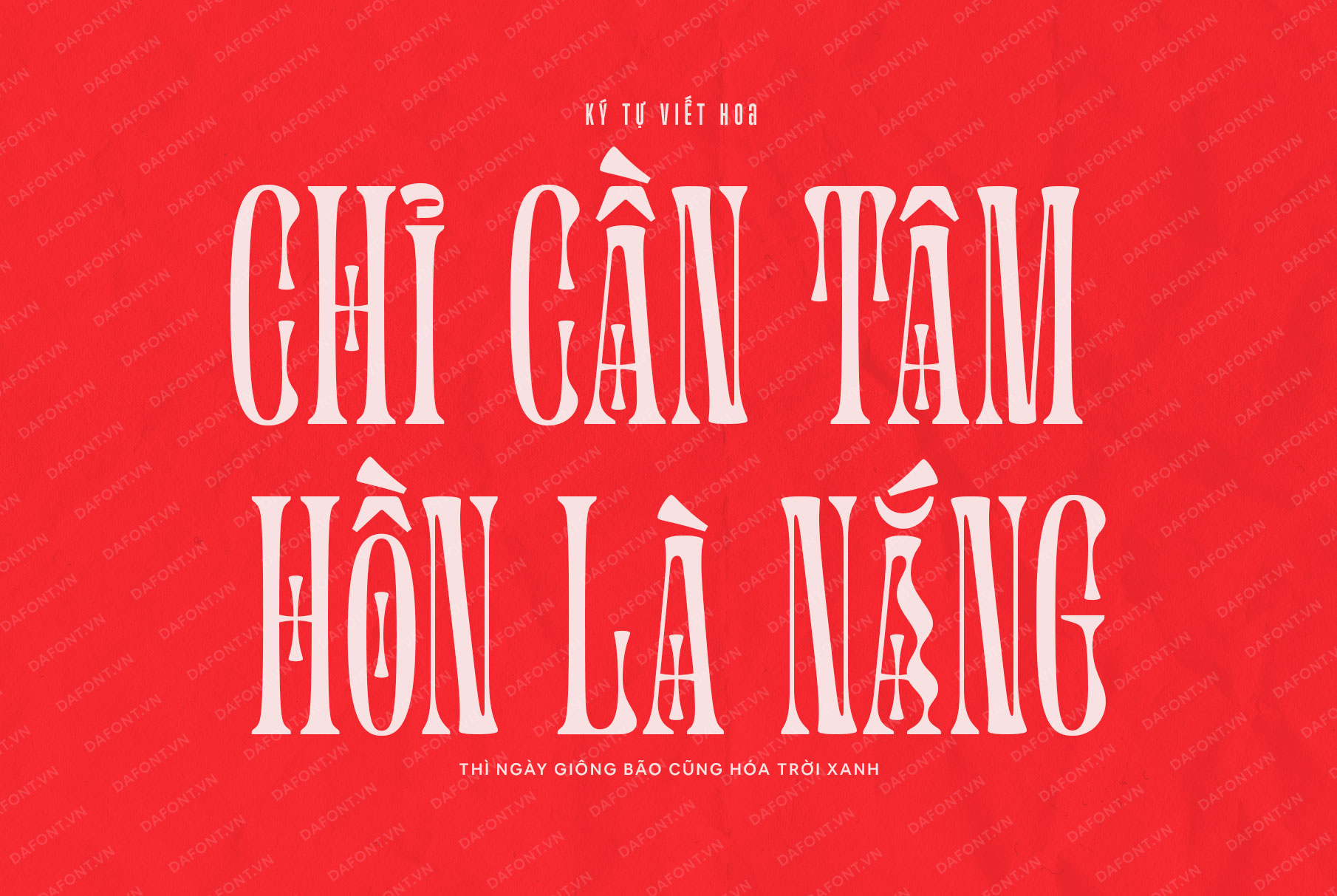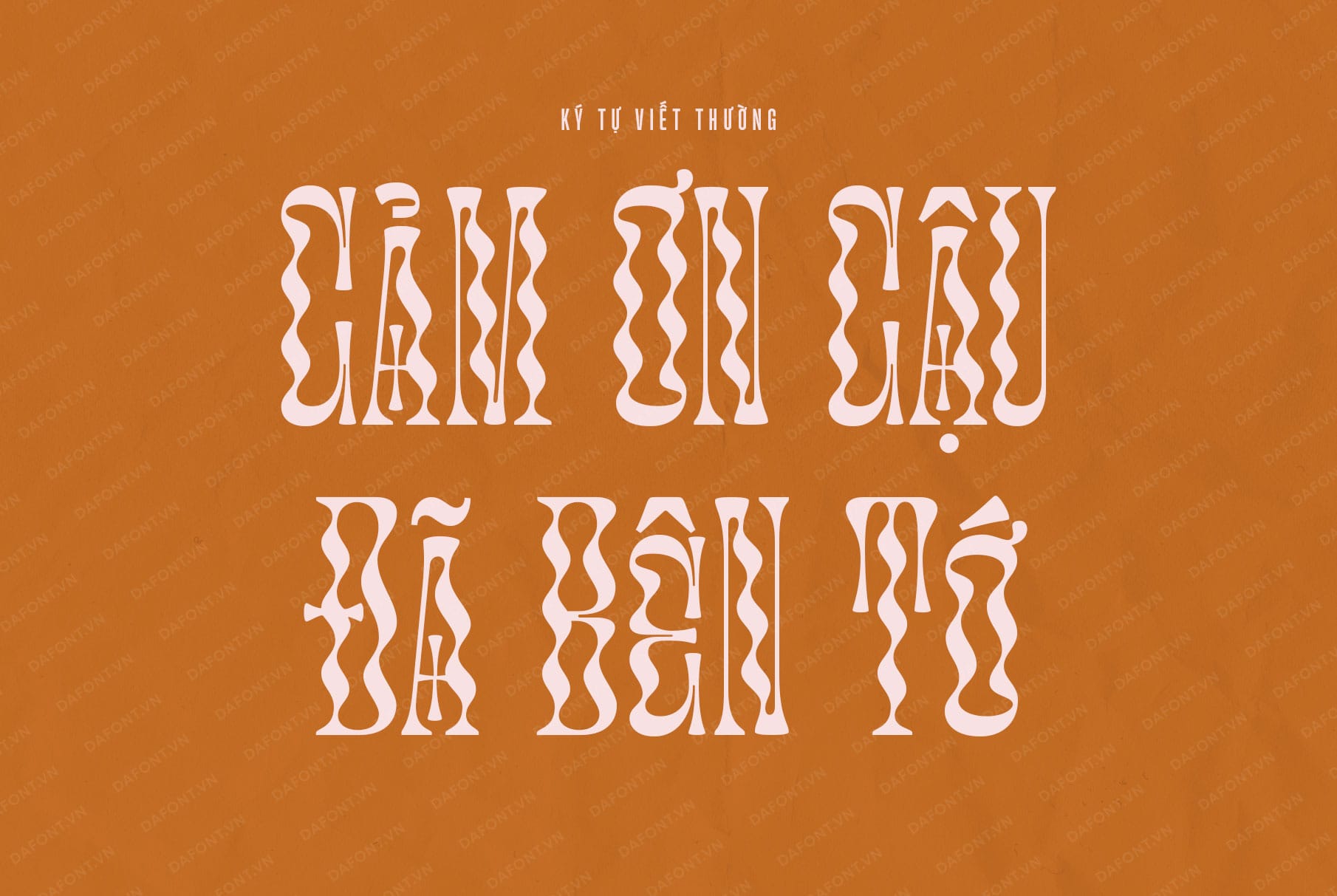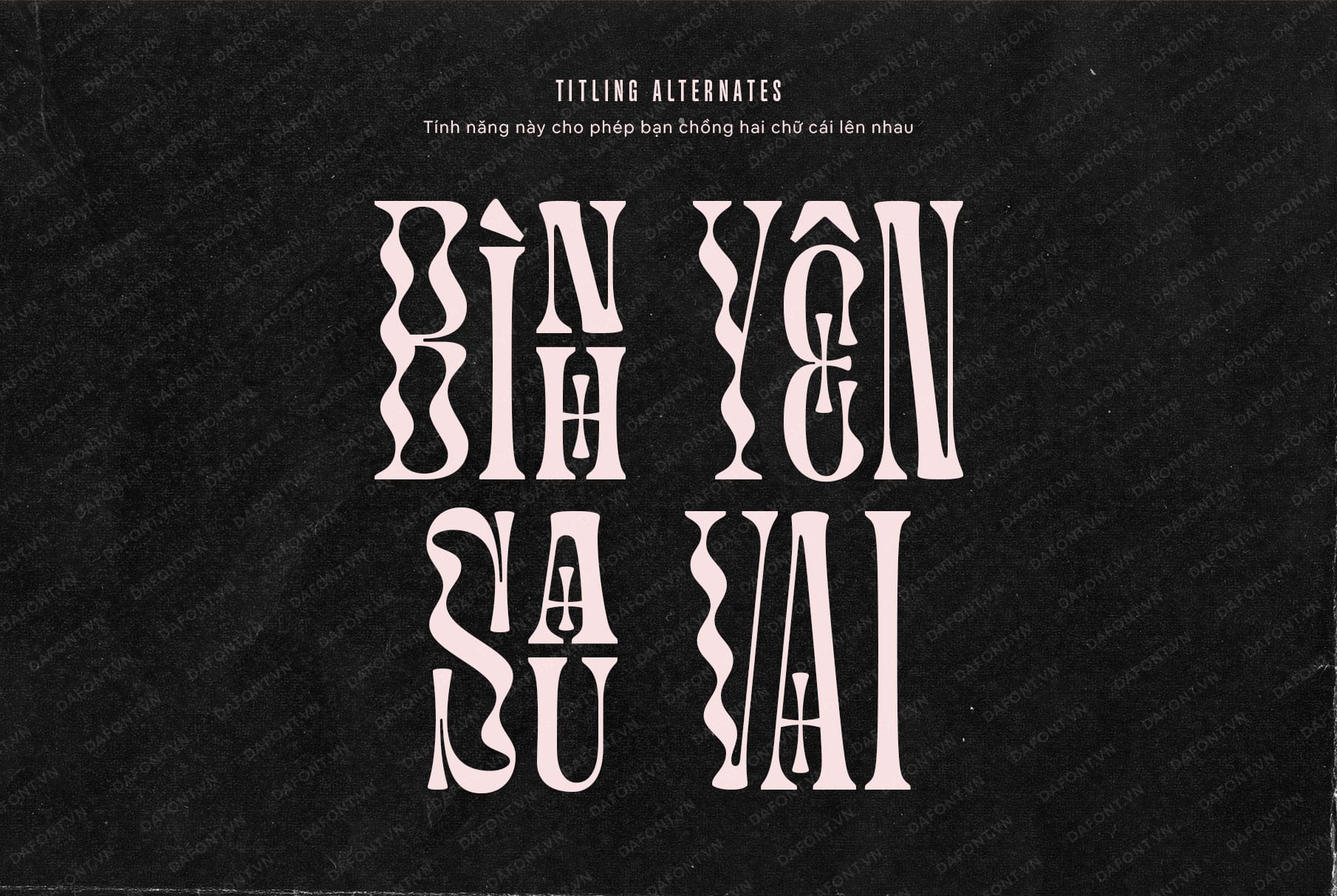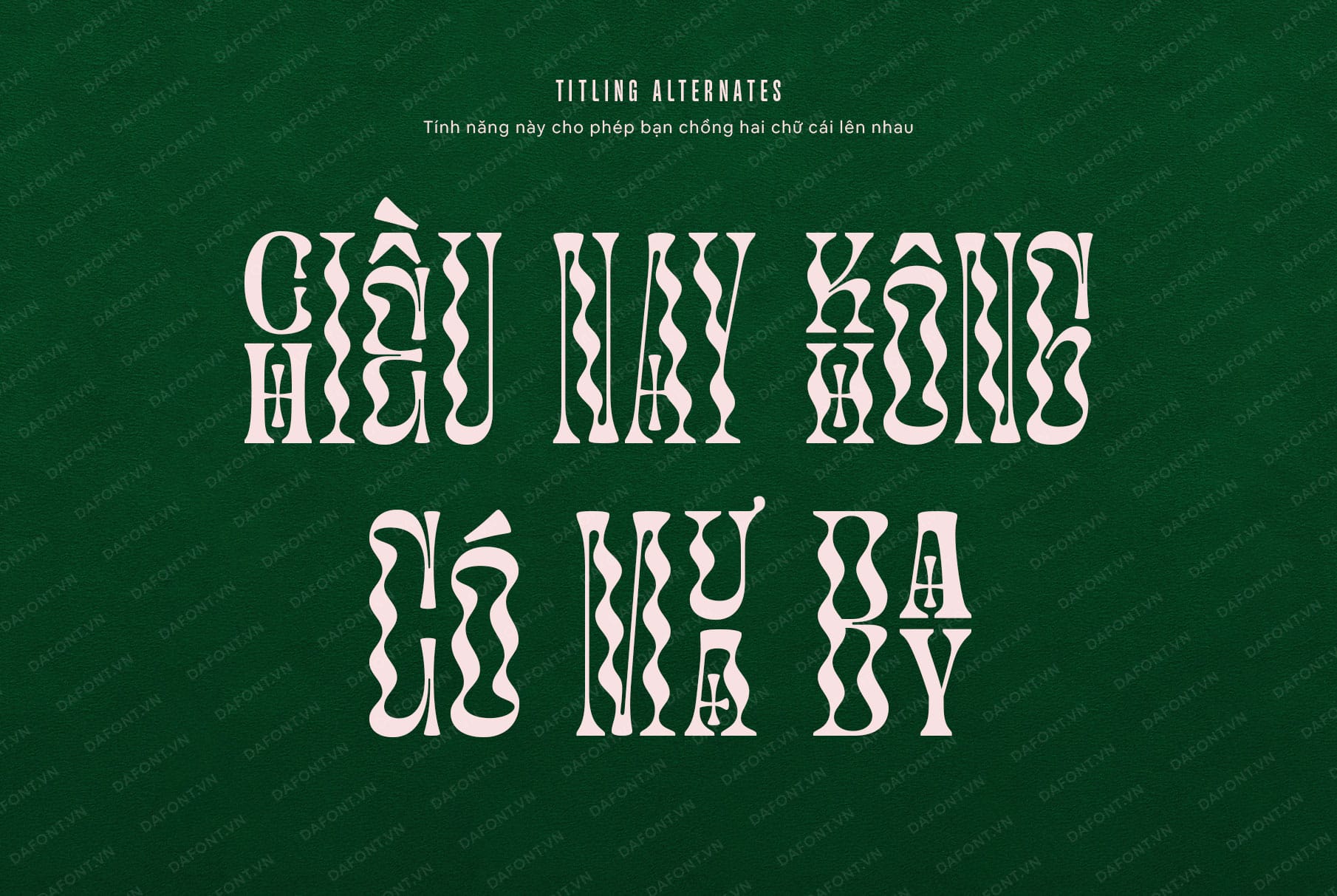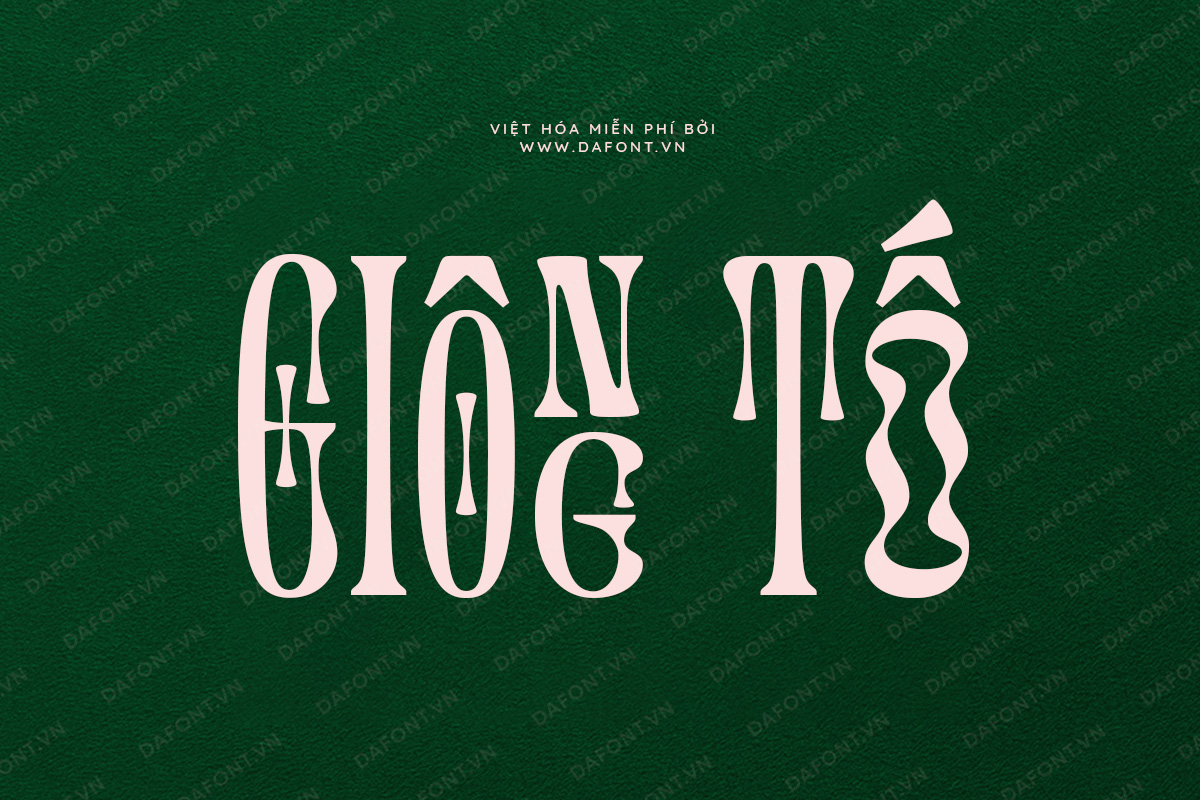
DFVN Glassure – Sự pha trộn hoàn hảo giữa cổ điển và hiện đại.
Glassure font là một kiểu chữ đầy cá tính và lạ mắt, kết hợp giữa sắc nét của các đường thẳng và nét uốn lượn tinh tế. Với phong cách sans-serif hiện đại, nhưng vẫn giữ được sự mềm mại và thanh thoát trong từng chi tiết.
Glassure được lấy cảm hứng từ từng đường kéo và uốn cong trong quá trình tạo ra các tác phẩm điêu khắc bằng thủy tinh, hoa văn đá cẩm thạch kỳ lạ nhưng đẹp mắt, với một chút phong cách nghệ thuật nouveau và cổ điển.
Điểm nổi bật của Glassure là các đường thẳng tắp và góc cạnh, sắc sảo kết hợp với với các góc bo tròn nhẹ nhàng, tạo nên sự cân bằng tinh tế giữa sự mạnh mẽ và duyên dáng. Ngoài ra, các chữ viết hoa và viết thường khác nhau có thể kết hợp để tạo ra một số điểm nhấn nhất định.
Một tính năng độc đáo trong kiểu chữ này cho phép bạn tạo khối hai chữ cái chỉ bằng cách chọn một số chẵn và các chữ cái bằng tính năng “titling alternates” để tạo ra 2 chữ cái lồng lên nhau đẹp mắt.
Không giống như các font sans-serif thông thường, Glassure mang đến sự kết hợp hoàn hảo giữa các nét mạnh mẽ tạo nên sự độc đáo và cuốn hút trong mọi thiết kế.
DFVN Glassure là lựa chọn lý tưởng cho các thiết kế muốn có sự nổi bật và phá cách. Phù hợp sử dùng làm logo, tiêu đề lớn, tạp chí, thiết kế web và poster quảng cáo. Sự tinh tế trong thiết kế của font chữ này giúp các thương hiệu dễ dàng thể hiện phong cách riêng.